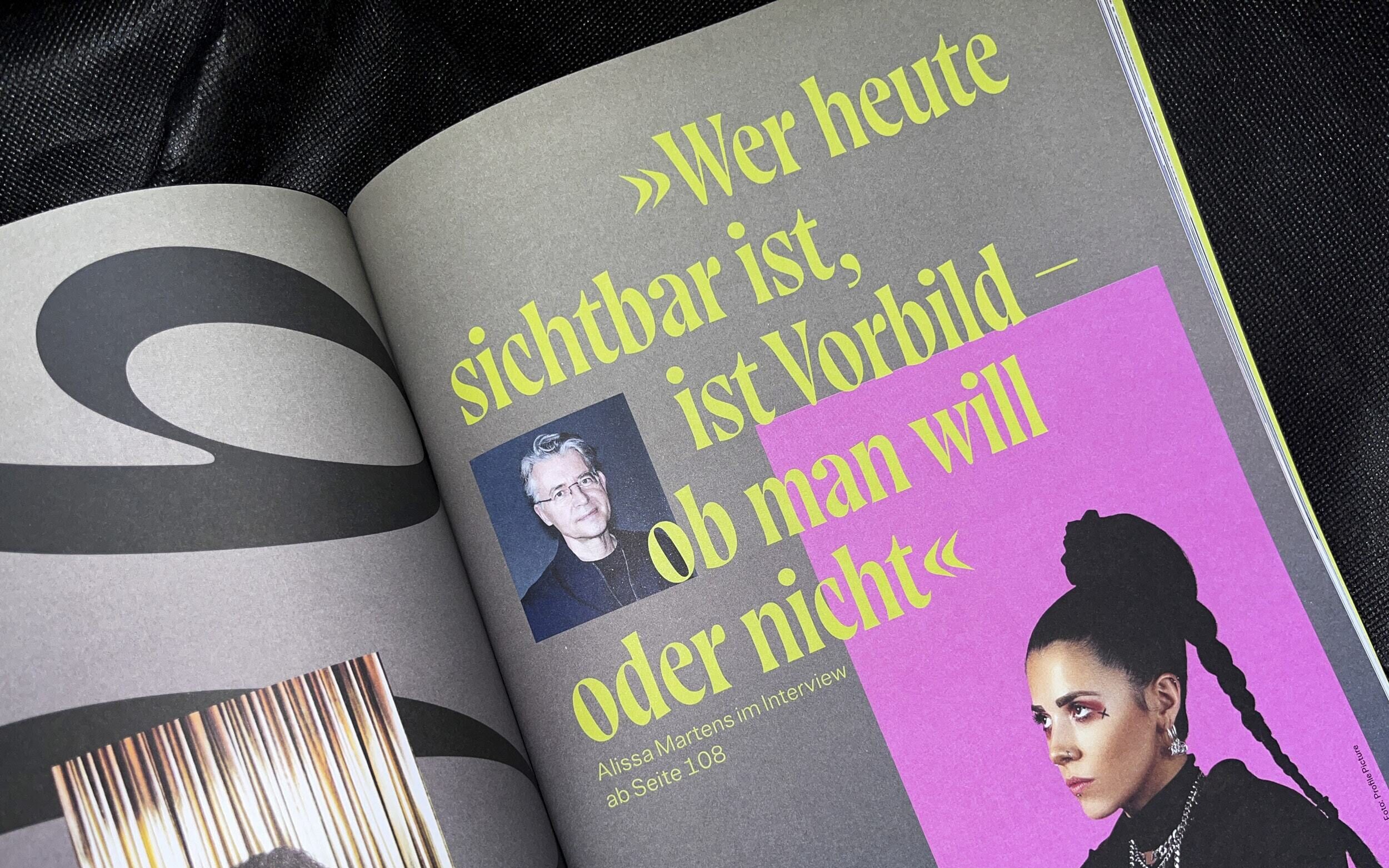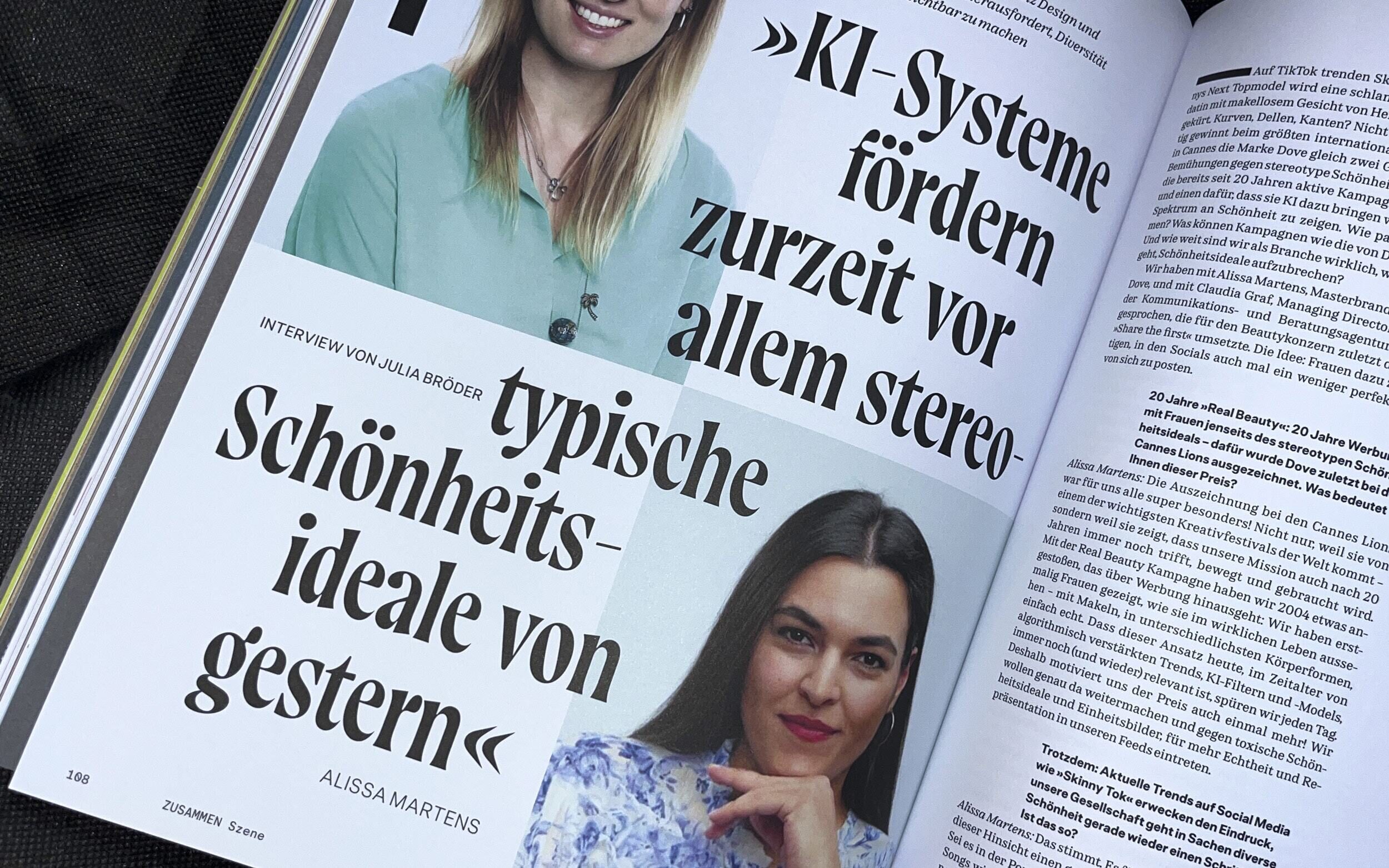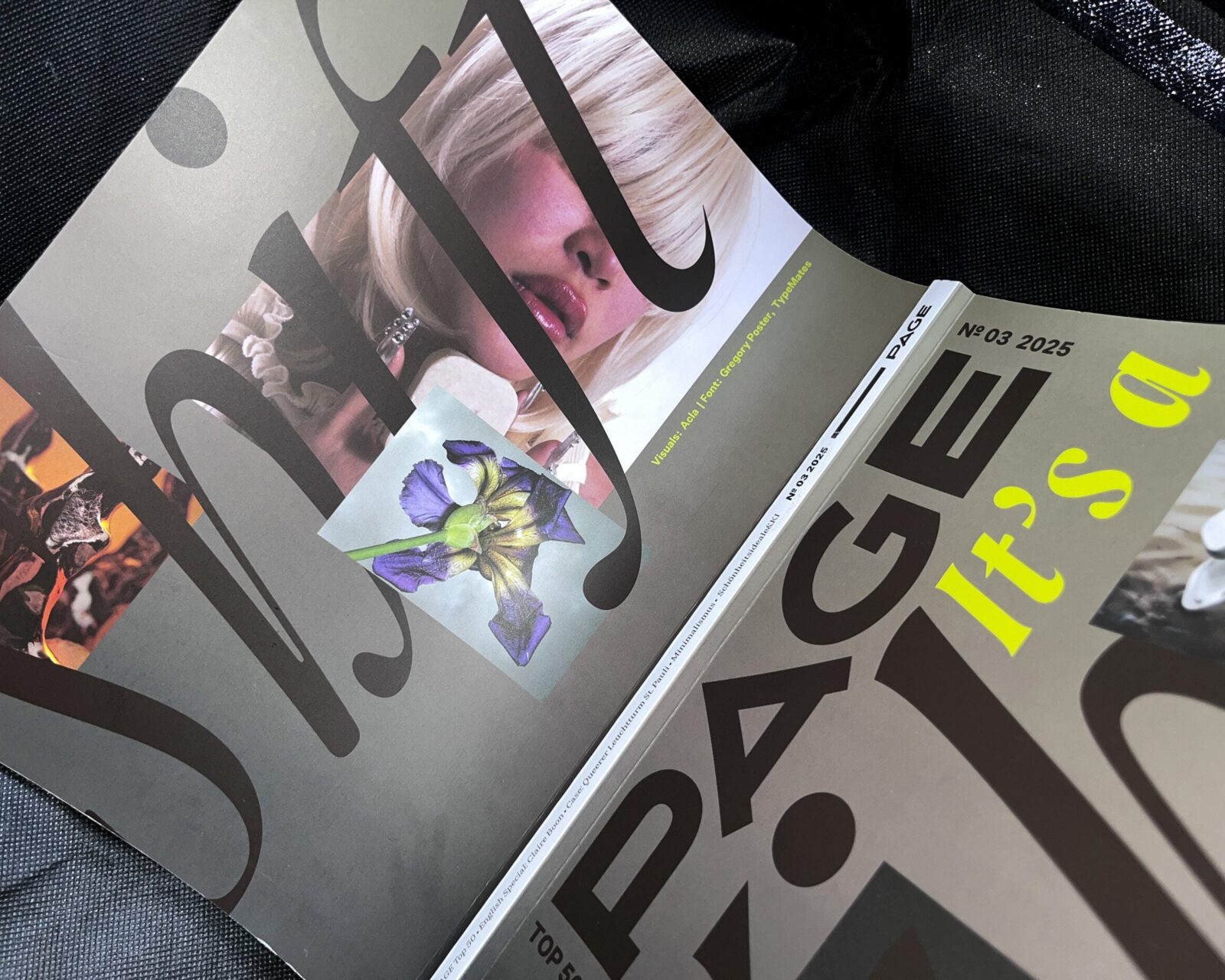
Gregory Poster
Wie ein kunterbunter Regenbogen, nur monochrom.
Gregory Poster ist eine wunderbar exzentrische Serif mit schillernder Persönlichkeit für inspirierende Gestaltung, natürliche Ästhetik und außergewöhnliches Storytelling. Sie überrascht mit plakativen Details und nostalgischer Anziehungskraft und bietet eine reizvolle Mischung aus scharfkantigen und sanften Momenten.
Sich von der Masse abzuheben erfordert Mut. Genau den beweist Gregory Poster: Lebendige Unregelmäßigkeiten schaffen Charakter und verleihen der Schrift ihre Einzigartigkeit. Statt mit glatter Perfektion überzeugt sie mit überspitzten Details und Authentizität. Gregory Poster ist kein Revival einer bestimmten Schriftart oder eines Genres, sondern vielmehr eine Ode an die analoge Druckproduktion und die Faszination aufgeschwemmter Buchstaben mit Quetschrand. Wie ein stilvolles Secondhand-Sofa weckt Gregory eine wohlig warme Erinnerung an eine frühere Zeit.
Ganz im eigenwilligen Charme der Vintage-Typografie zeigen sich die horizontalen Stamm-Serifen als sanft auslaufende, leicht gekehlte Strichenden. In Kombination mit dem unmissverständlichen Strichstärkenkontrast und einer stark geneigten Schattenachse entsteht durch die kopflastigen Buchstabenformen ein überschwänglicher, fast schon barock überladener Flair mit erfrischenden Anomalien.
Die ergänzende Kursive sorgt ebenfalls für eine intensive Auszeichnung durch den ausgeprägten 18° Winkel und eine fließende Konstruktion. In der monochromen Welt der Buchstaben setzt Gregory Poster farbenfrohe Akzente.
Mit Griechisch und Kyrillisch, exklusiv von Muttersprachlern gestaltet, umfasst Gregory Poster mehr als 270 Sprachen, einschließlich Vietnamesich. Sorgfältig produziert und ausgestattet mit einer Reihe von OpenType-Features für anspruchsvolle Typografie und einer Auswahl an Ziffernsätzen, sprachspezifischen Varianten und feinen Symbolen und Emojis.
Verbunden im Herzen, anders im Detail: Gregory Text und Gregory Grotesk harmonieren ideal mit der Gregory Poster. Alle drei versprühen eine ähnliche positive Energie und überzeugen mit freundlichem Enthusiasmus, setzen mit ihrer eigenwilligen, voneinander unabhängigen Gestaltung jedoch verschiedene Akzente.